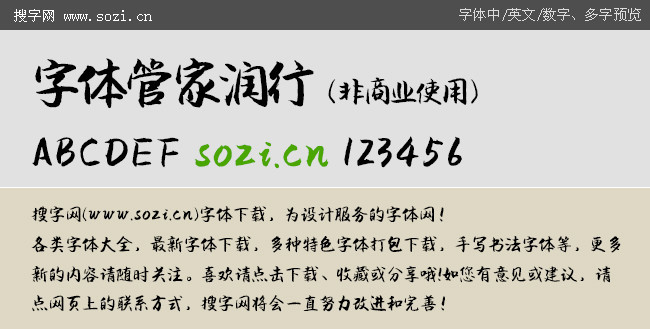
字體管家潤行(非商業(yè)使用)
搜字網(wǎng)給大家提供一款字體管家潤行(非商業(yè)使用)中文字體下載,該字體是一款手寫中文字體,這款字體端莊,書寫簡潔大方,適合包裝設(shè)計(jì)、書裝設(shè)計(jì)、海報(bào)設(shè)計(jì)等應(yīng)用(此字體為個(gè)人非商用版,商用可以聯(lián)系QQ:1006760504)。